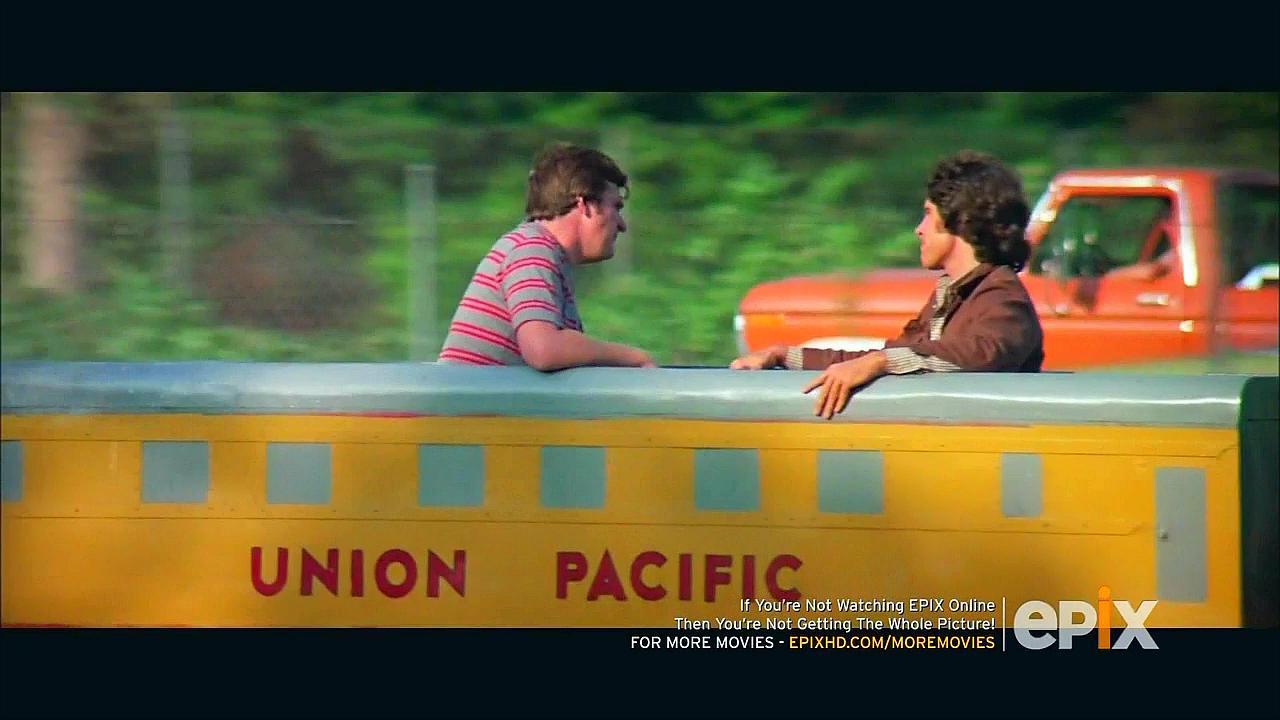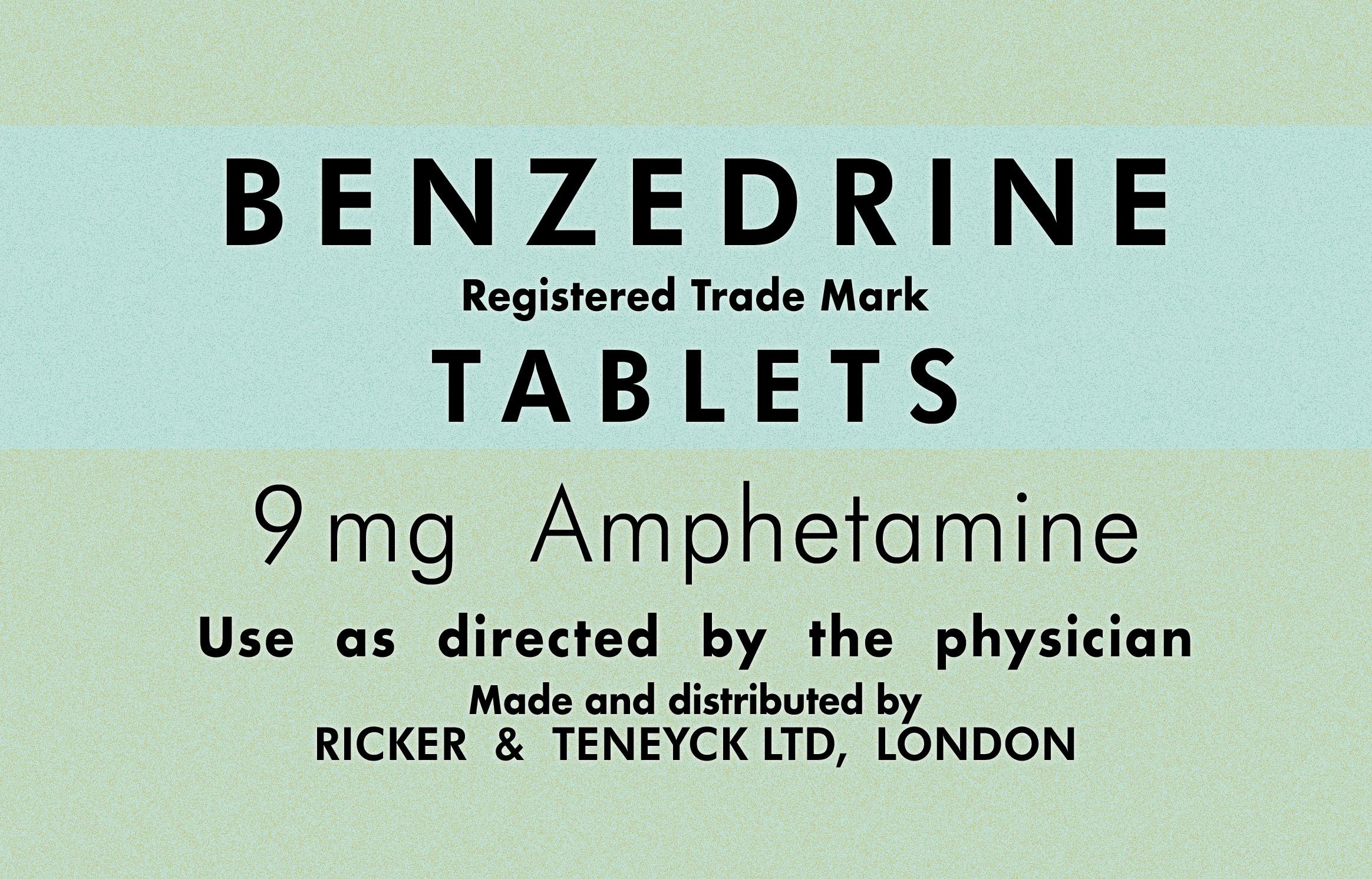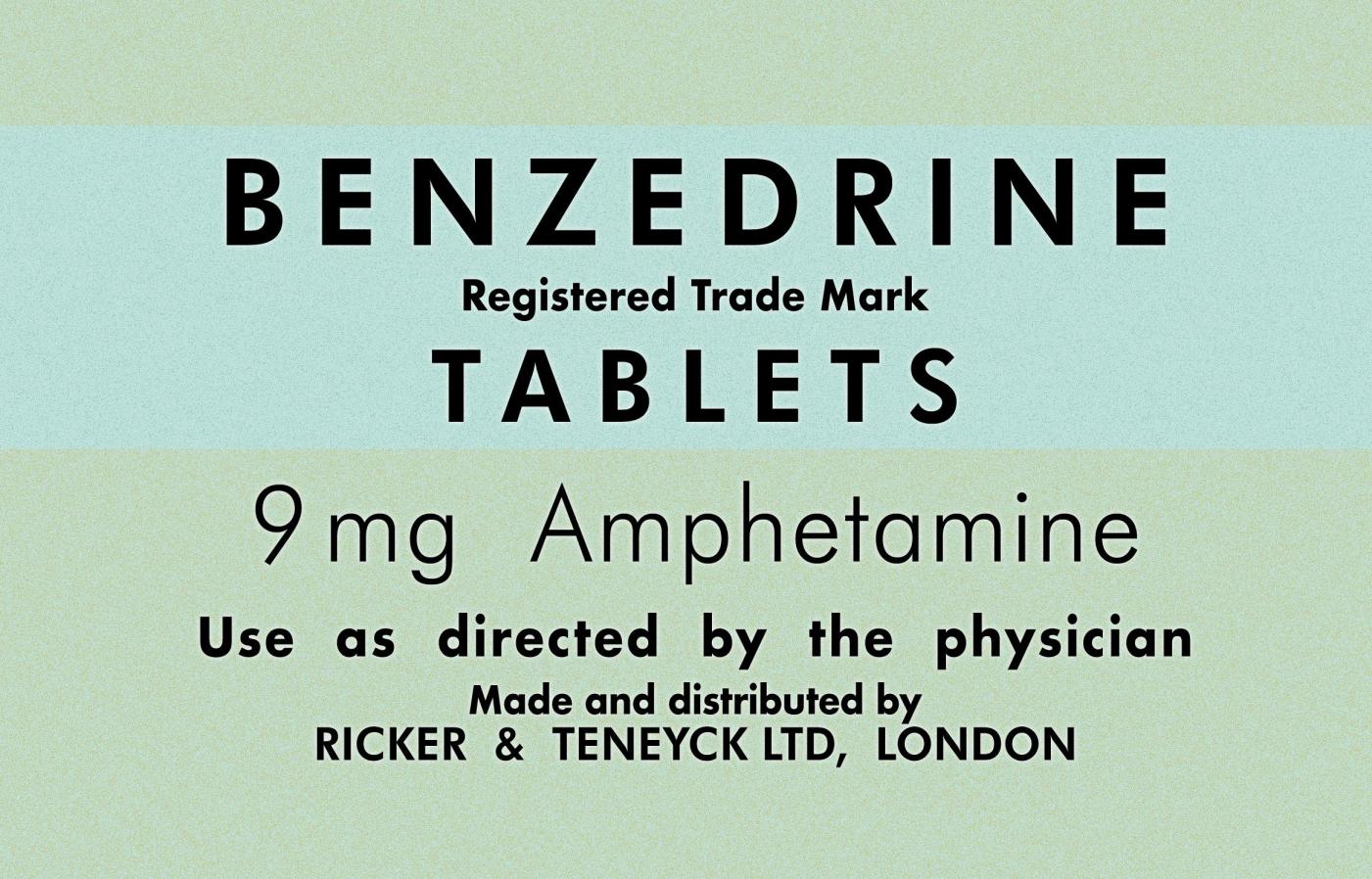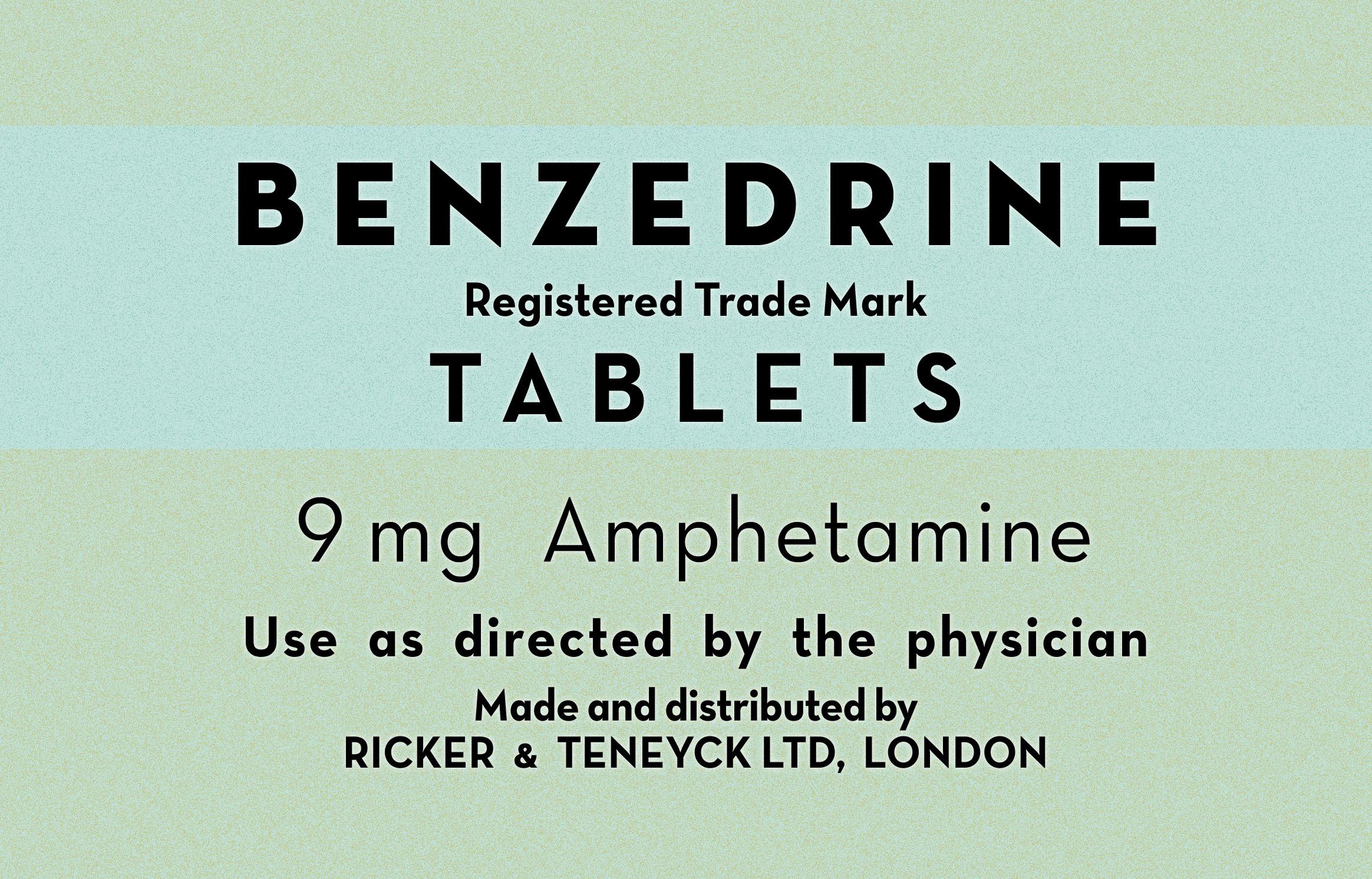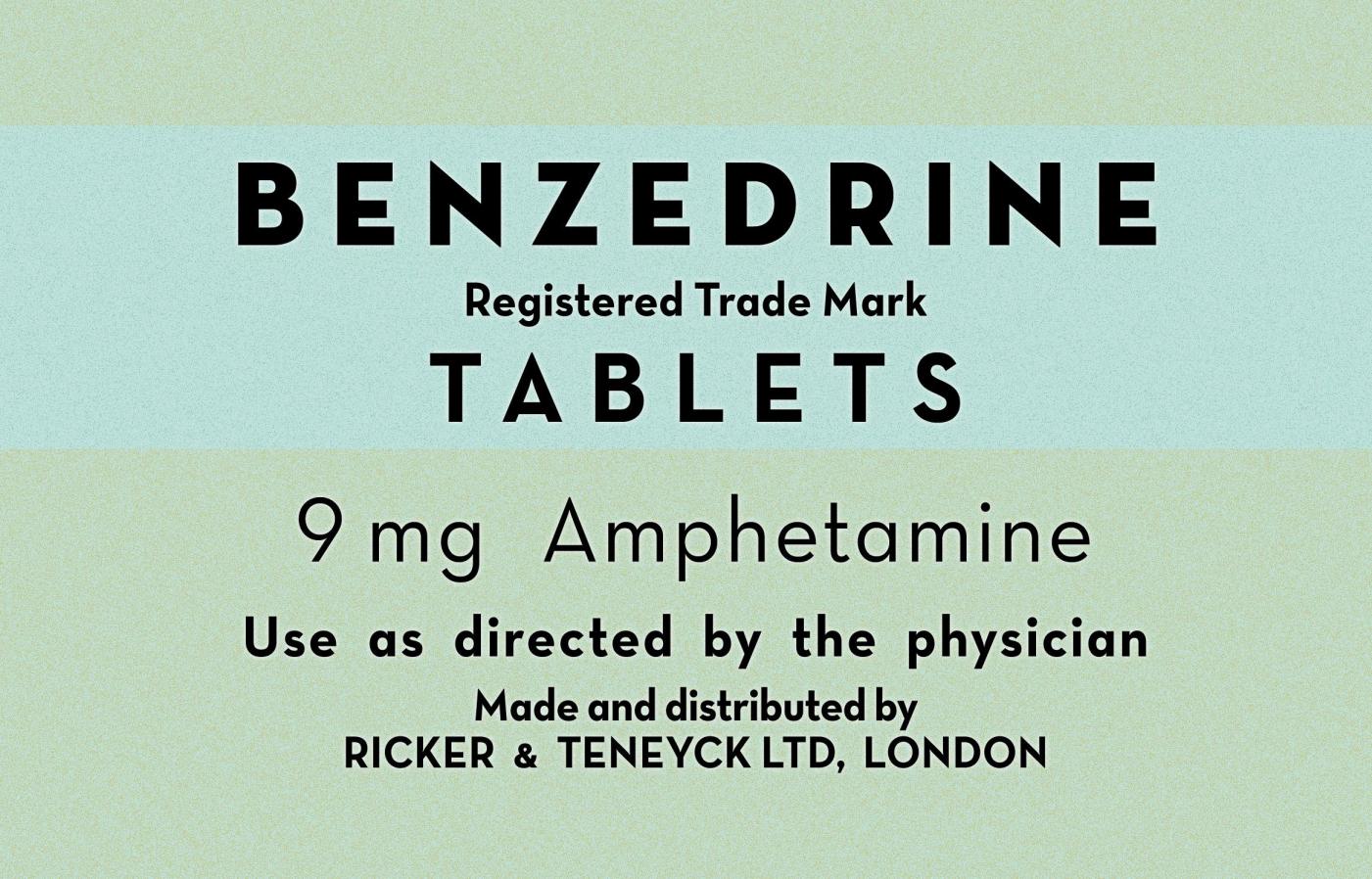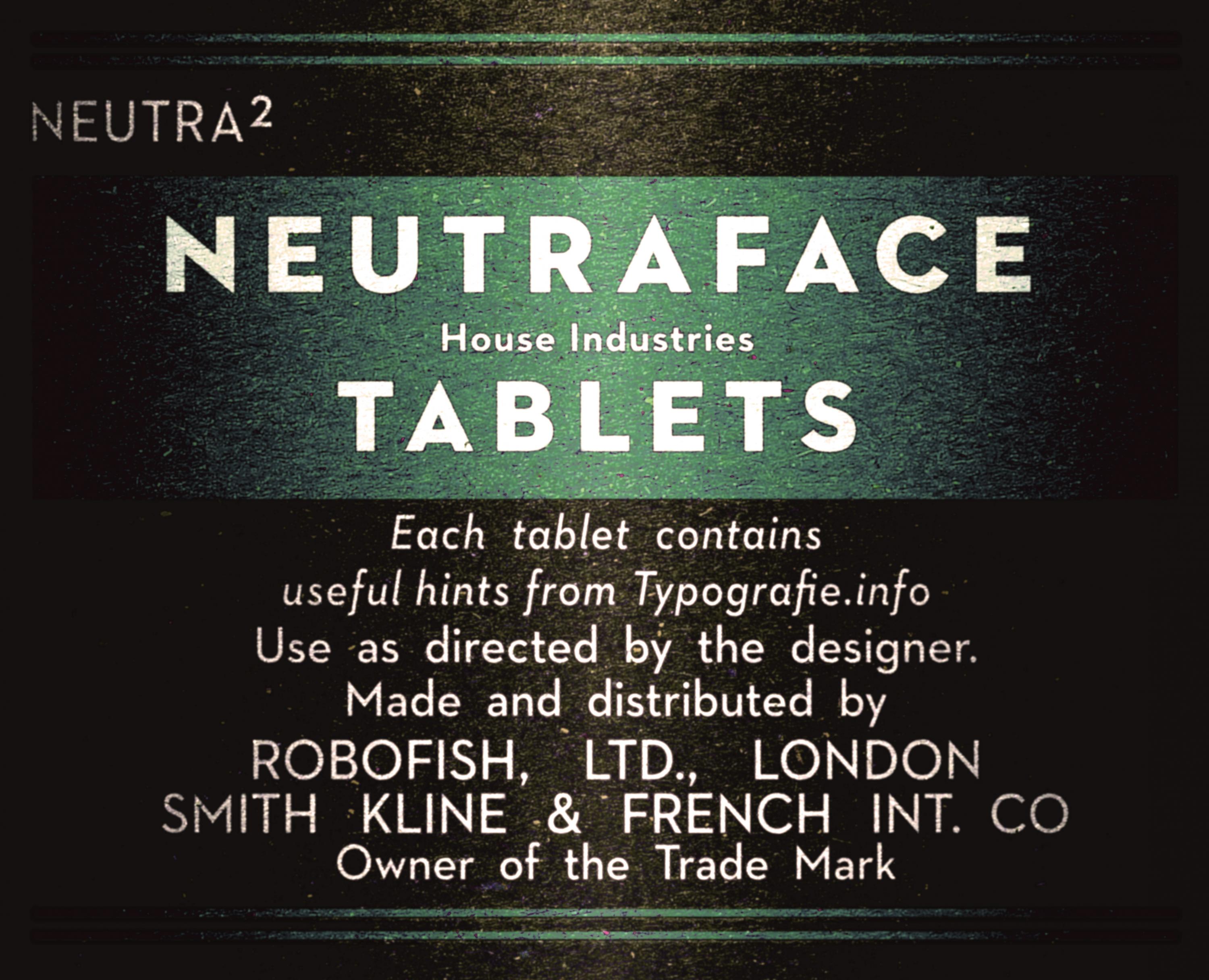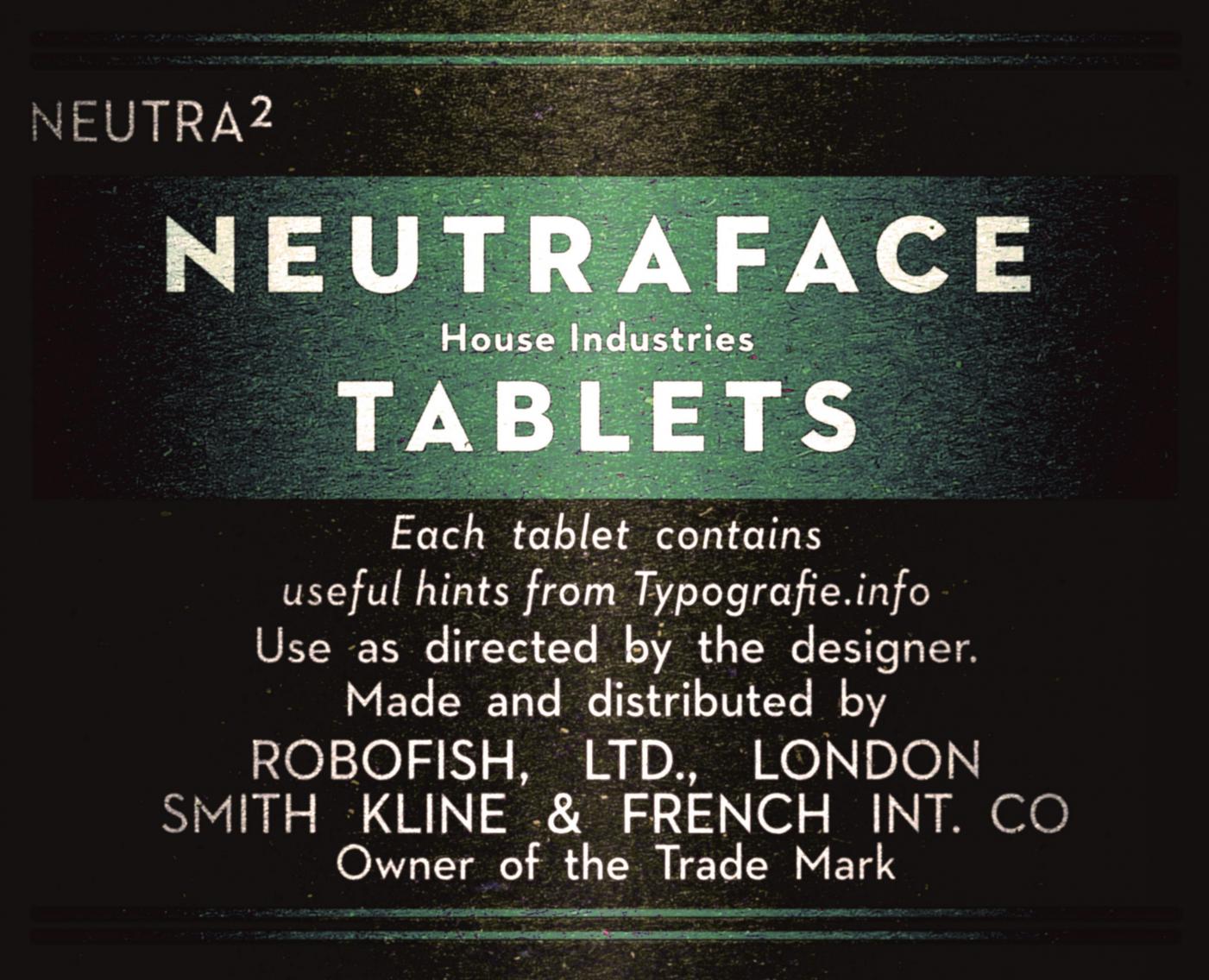
Serifenlose Fettschrift 40er -60er Jahre
Immer wieder scheitere ich beim Nachsetzen von älterer Werbung aus dem angelsächsischen Raum (Prospekte, Umverpackungen, Beipackzettel) an dieser Schrift.
Spontan sehe ich eine Futura bold (extra, super), jedoch verlieren diese Stärken den spitzen Charakter. Auch das C und einige Proportionen gehen eher in Richtung Century Gothic, und auch hier verschwinden die Spitzen, sowie man bold wählt.
Daher meine Frage: kennt jemand digitalverfügbare Vorläufer / Varianten der Futura, die den stacheligen Aspekt bis in die sehr fetten Schnitte fortführen?
Leider nicht ganz so fett, wie ich ihn gern hätte, aber viel besser als Futura Md BT. :)
Bin gerade noch auf die Neutraface Titling gestoßen.
Schriften dieser Art sind ab der zweiten Hälfte der 1920er in Deutschland entstanden und hipp geworden. Hier ein sehr markantes Beispiel: Bahnhofsfutura von Paul Renner aus dem Jahr 1926: https://www.kai.gs/bahnhofsfutura/
Viele dieser geometrisch konstruierten gab es als „spitze“ und „stumpfe“ Schriften. Ein Beispiel wäre die Erbar Grotesk, ich finde da aber auf die Schnelle kein Schriftmuster mit den beiden Ausführungen der Lettern A, M und N. Die Schrift ist also eine spitze, geometrische und fette Grotesk. Das Verlieren der Spitzen kann als eine neumodische Erscheinung betrachtet werden.
Die verwendete Schrift basiert also auf Schriften wie der Bahnhofsfutura oder der spitzen Erbar und nicht auf der bekannten Futura. Es gibt eine nicht unerhebliche Zahl von Schriften dieser Art, gelegentlich auch in AllCaps. Du kannst by Myfonts nach sogenannten Tags suchen. Diese wären für diese Schrift: geometric, sans, german, 1920s ...
Von der Erbar aus kann man dann nach ähnlichen Schriften suchen ... Viele Schriften basieren zwar auf der Erbar Grotesk, aber das wird gerne verschwiegen.
Auch ganz interessant ist in diesem Zusammenhang die Neutra-Schriftfamilie von Richard Neutra (2002):
Die Neutra Display Titling passt auch ganz gut ... Es gab hier im Forum vor vielen Jahren schon mal Diskussionen zu diesen spitzen Schriften. Ich bin aber zu faul nach diesen Diskussionen zu suchen. Aber in groben Zügen sollte das reichen die Schrift einzustufen.
Mit der Neutra bin ich dir allerdings schon zuvorgekommen. ;)
Der Fließtext könnte in einer Erbar Grotesk sein und ggf.  basiert das Logo auf der spitzen und fetten Erbar.
Das ist möglicher falsch, siehe das kleine a.  Das gab es zwar IIRC auch so als alternativen Buchstaben in der Erbar Grotesk, es könnte aber auch so was wie die Super Grotesk (Arno Drescher, auch Drescher Grotesk genannt) sein.
The Pearl Harbor logo was used on a number of war effort posters and the 1942 timetables between January and April. This logo was in the process of full implementation, but its rollout was cut short by Union Pacific President W.M. Jeffers. On April 18, 1942, Jeffers directed that the logo be returned back to the old Overland logo, though it would "entail quite an expense" to do so. The Pearl Harbor logo never appeared on any locomotives or rolling stock.
Aha? Der Schriftzug ist als auf dieser Werbekampagne raus genommen ... Da robben wir uns also langsam ran ...
Fließtext: kleines a nicht ausfürhlich genug beachtet ...
Und letztlich hab ich auch noch was anzubieten:
Diese Schrift ist hier ist eigentlich auch aus einem Forenbeitrag entstanden, damals als Minimalfont mit nur einer Hand voll Buchstaben. Es ging damals übrigens um einen Stasi-Aktendeckel, der für ein Filmprojekt nachgebaut werden sollte, da habe ich dann nur schnell die benötigten Buchstaben nachgezeichnet und in den Font gepackt, damit erklärt sich dann auch der Schriftname :-)
Aber vielleicht passt sie als spitze Grotesk ja auch hierfür? (Sie ist allerdings noch nicht so ganz fertig, zu ein bisschen muss ich daran wohl noch feilen, daher ist das hier die erste Veröffentlichung der komplettierten Schrift.)vorgang-muster.jpg
Ich erkläre mal die Neutra zum Sieger. Sie ist nicht in allen Punkten identisch, aber sie hat genau diesen hochgezogenen Look und den biederen tiefen Schwerpunkt, und die Spitzen bleiben schön erhalten. Damit kann ich eine Menge anfangen, wenn Futura schon wieder zu aufgeräumt und modern wirkt. Die hilfreichste Antwort zu markieren fällt mir nun etwas schwer, daher danke ich euch allen und bin mit meinen neuen Fonts sehr glücklich.
Mein eigener Futura-Nachbau kommt proportionsmäßig schon ganz gut hin, wirkt aber zu frisch. Lasse ich hingegen die Neutra drüberlaufen, entfaltet sich der ganze Grusel wunderbar. Mit der Neutra werde ich noch viel Vergnügen haben.
Nichtsdestotrotz sollte man der Erbar wieder viel mehr Beachtung schenken.